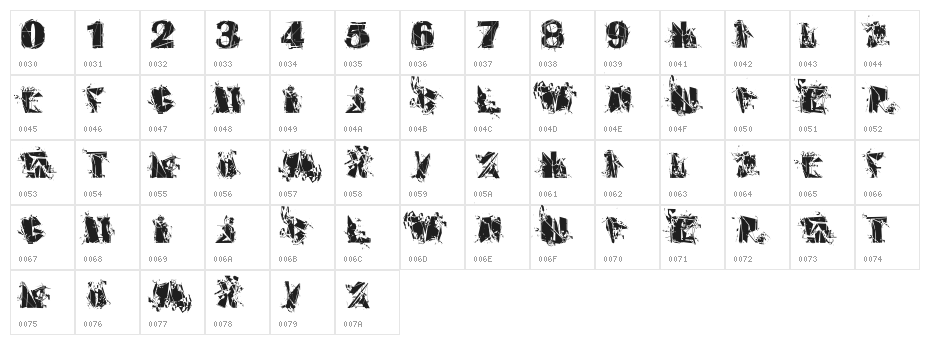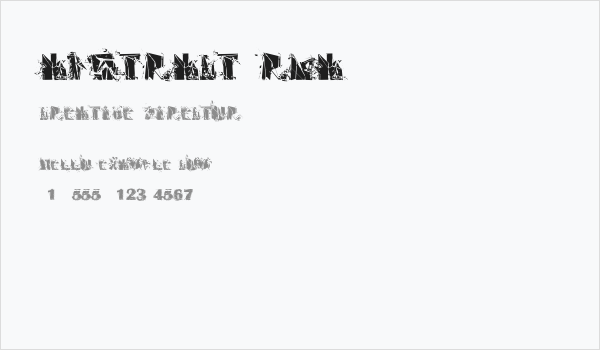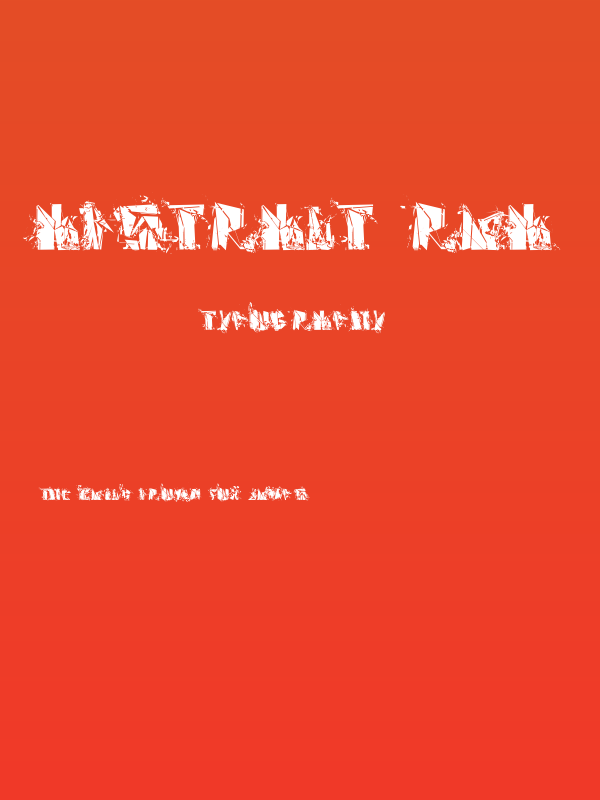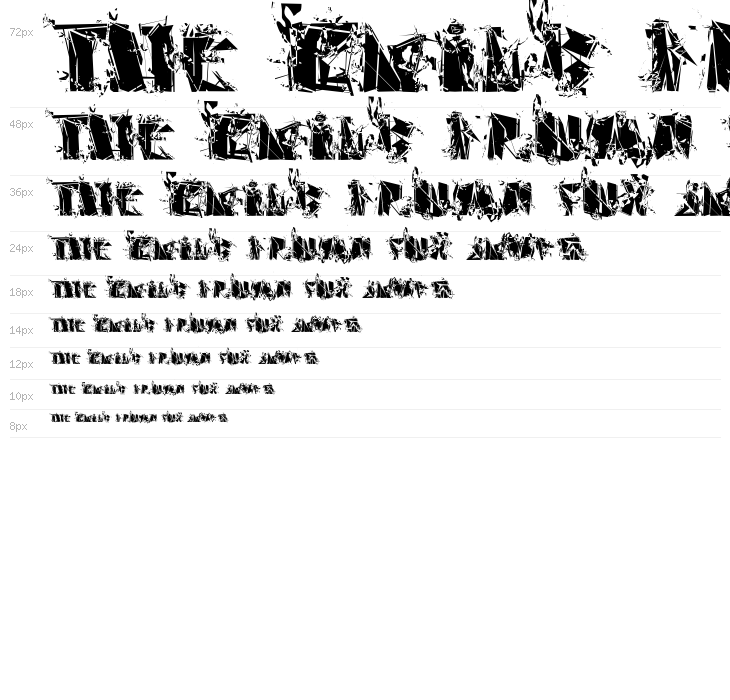
Abstract Rua Font
| Style général | Modern, Urban, Grunge |
| Projets proposés | Ideal for projects that require a bold and rebellious aesthetic, such as album covers, streetwear branding, graffiti art, and edgy posters. |